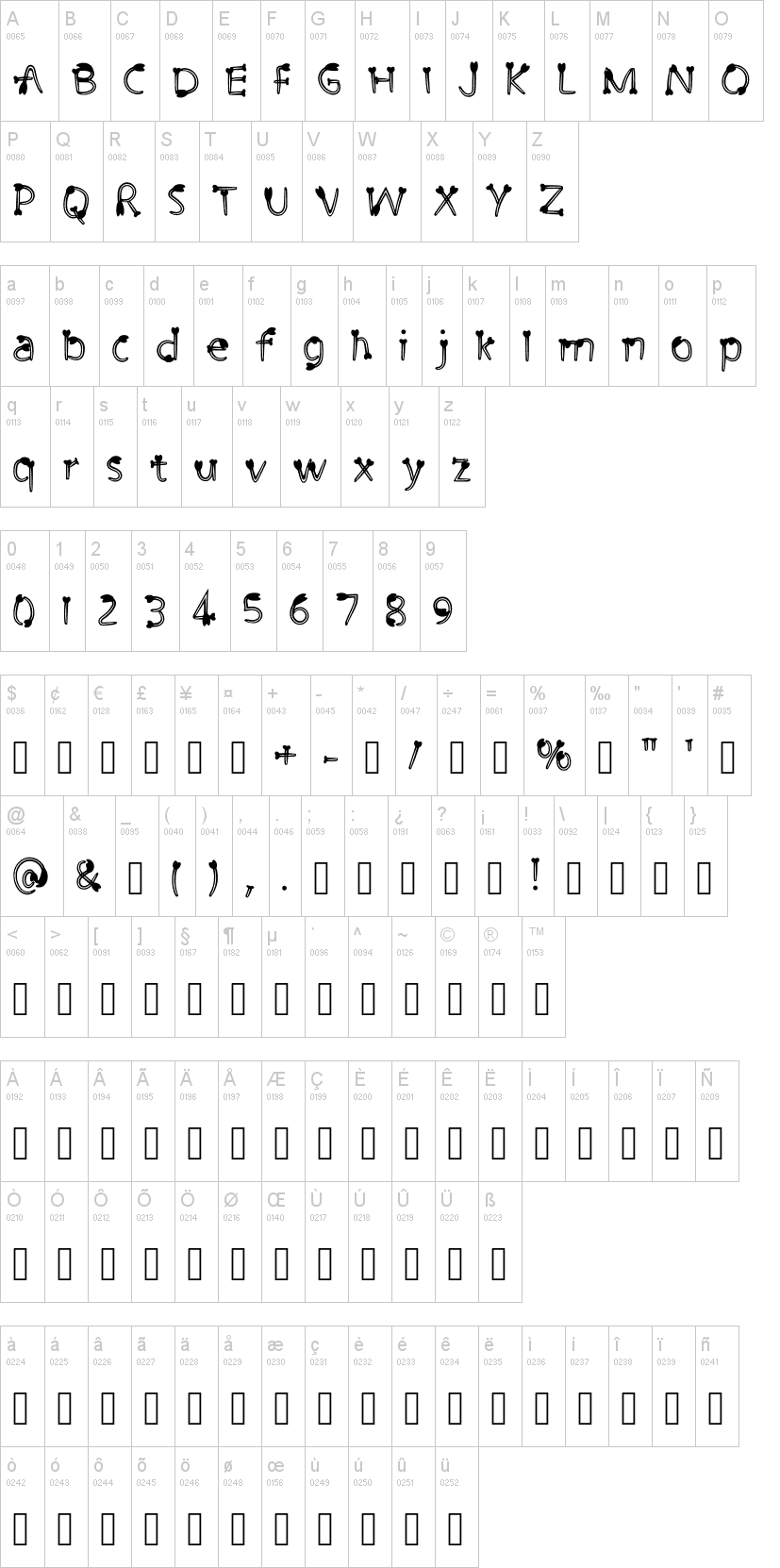
Cutie Pie
Cutie Pie 字体是一款可爱的英文手写体字体,由美国设计师Cristina Pagnotta创作。它具有温柔、可爱、活泼的特点,适合在各种类型的设计中使用,如海报、书籍、电影题材等。字体的外观是由温柔的曲线和小折痕组成的,整体看起来柔和可爱。
Cutie Pie是一款非常不错的手写艺术字体,具有很好的视觉感,适合于文化类的宣传设计、商业类品牌的广告和产品包装设计以及个性化文字排版等较多场景。
Cutie Pie字符映射图